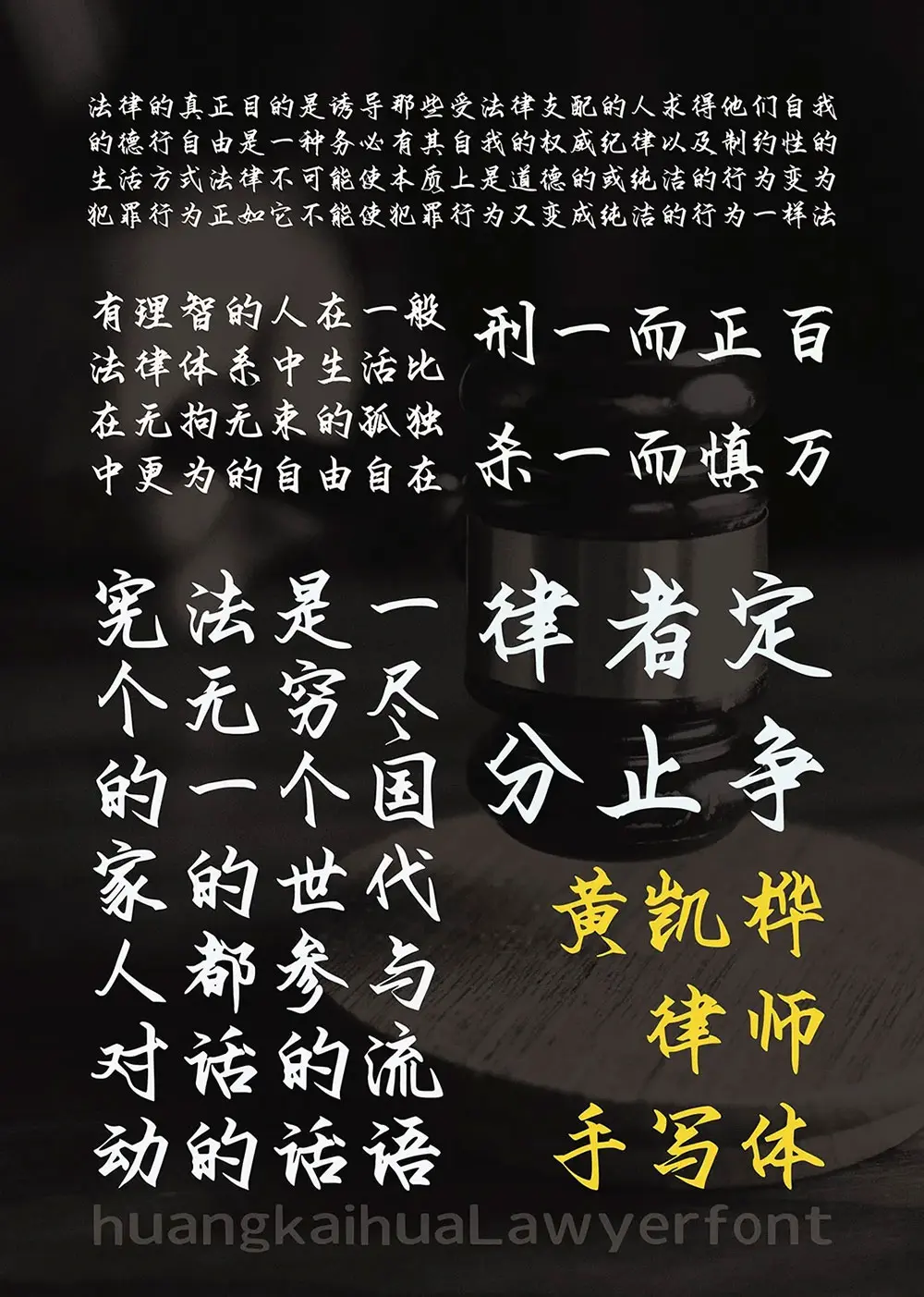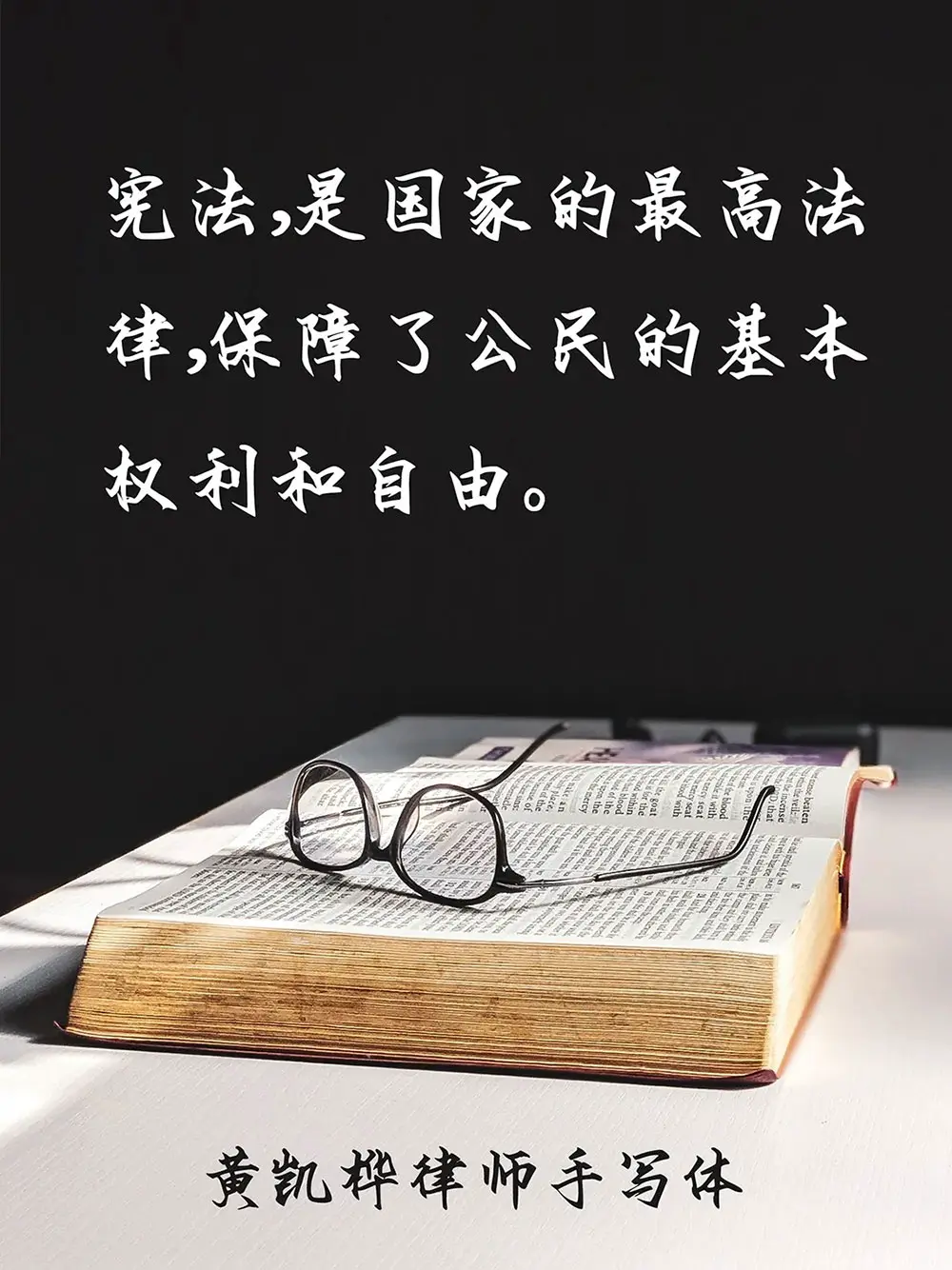
近年來,團隊和本人在業務和生活中,接觸到越來越多的企業因為字體侵權而蒙受損失的事情。
作為一名律師,對於字體使用事宜,一是尊重知識產權的維權。因為一套字體的產生,需要耗費大量的人力、時間和費用。但對很多企業來說,字體商業授權費用是一筆不小的費用;二是很多當事人不知道哪些字體可以免費商用哪些不能,以至於侵權或迷茫。
為此,機緣巧合之下,在諮詢公司的幫助下,以本人美工筆手寫字為基礎,製作了這一套字體。基於對作者版權和律師行業的尊重,命名為“黃凱樺律師手寫體”。
也許,這是國內律師行業第一套免費可商用中文字體。
黃凱樺律師手寫體簡介:黃凱樺律師手寫體(作品登記證書登記號:陝作登字-2024-F-00013739),是一套根據簡體中文漢字編碼國家標準(GB2312編碼)設計的字體,並在此基礎上一共設計了6769個簡體漢字,為一款原創字體,具有其獨特的字形風格,適用於廣告、書籍、海報等多個場合。
希望通過這套字體,讓更多的企業、組織和設計師設以及其他相關人員,瞭解到字體的合法使用,也可以多一套可以免費商用的字體,少一些侵權風險。